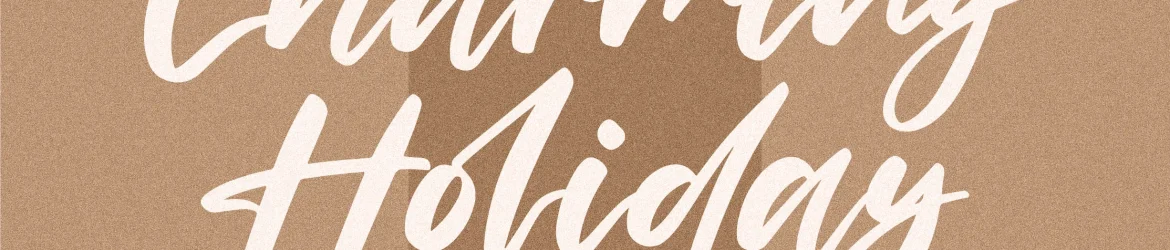
A Charming Holiday Font é perfeitamente adequada para projetos que exigem um toque handwritten elegante e autêntico. Seja para logos e projetos de identidade, designs de móveis de casa ou embalagens de produtos, a fonte da perspectype traz um charme único aos seus projetos. A Charming Holiday Font é perfeita para criar um design cuidadosamente detalhado nas etiquetas das embalagens, cartões de presente e até mesmo nas caixas personalizadas dos livros. Além disso, ela é ideal para adicionar um toque romântico aos posters de eventos especiais ou mensagens personalizadas em sua próxima campanha publicitária. Com seu estilo autêntico, a Charming Holiday Font é perfeita tanto para designers profissionais quanto para amadores que procuram uma fonte handwritten com um brilho único e elegante.